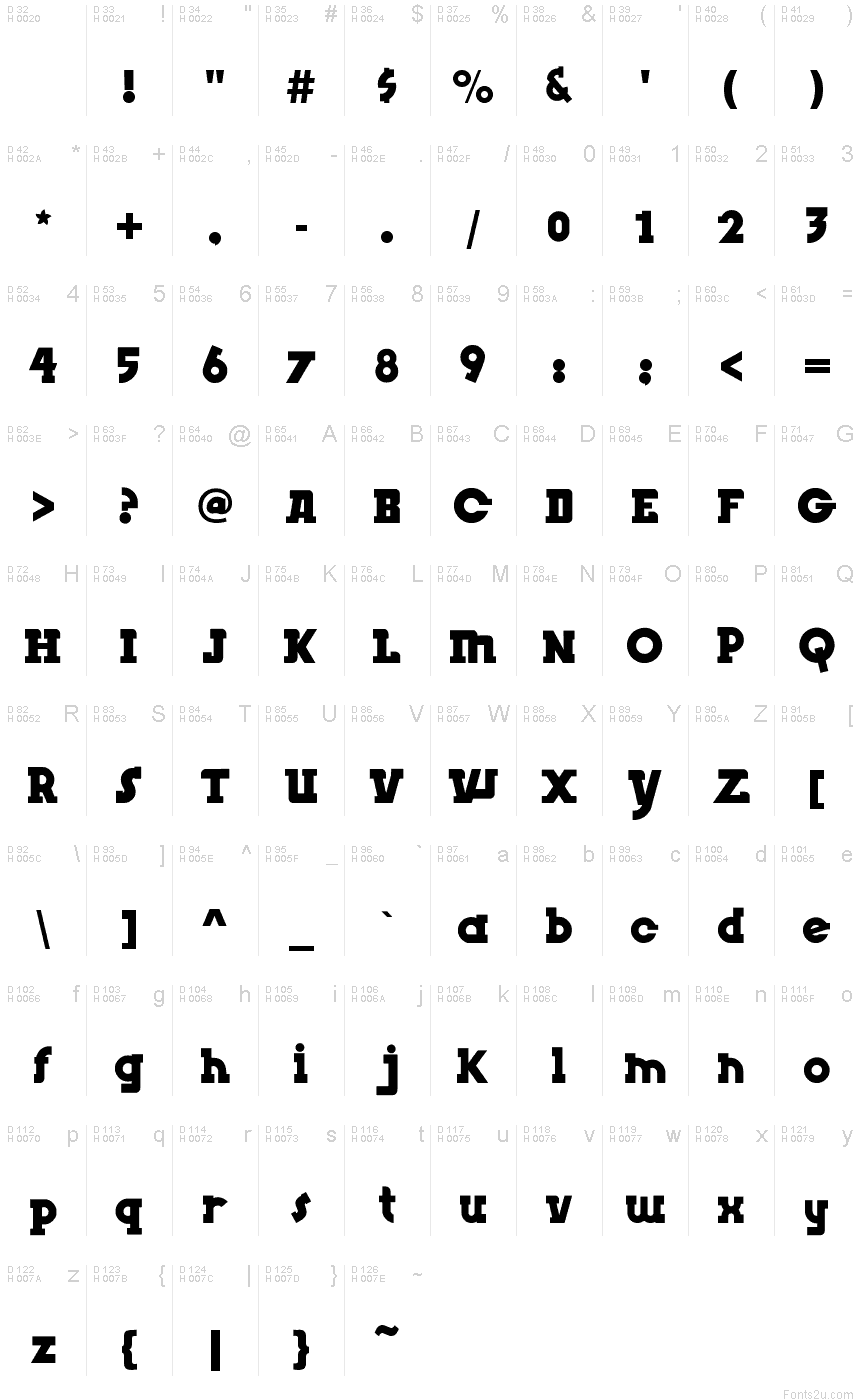
Insight Issue od Galdino Ottena je bezplatné starosvětské display písmo typu slab serif, které je vystavěno z masivních, těsně k sobě přiléhajících velkých písmen. Široké tahy a tupé obdélníkové serify dodávají sazbě hustou, plakátovou siluetu. Náhlé přechody mezi křivkami a rovnými hranami brání tomu, aby tato pevná konstrukce působila mechanicky.
Umožňuje vytvořit působivé nadpisy inspirované starými vývěsními štíty a ručně řezanou reklamou. Díky tomu je přesvědčivou volbou pro hudební plakáty, branding streetwearu a merchandise akcí s drsným retro nádechem. V obalovém designu se široké tvary písmen mohou stát součástí odznaků nebo etiket namísto neutrálního produktového textu.
this font was conceived with the intention to make possible to creative of advertising and design the freedom to create title of texts, short texts, logotypes, marks, and any another artistic work being able to modify each letter with the purpose to personalize its work in accordance with its infinite creativity.